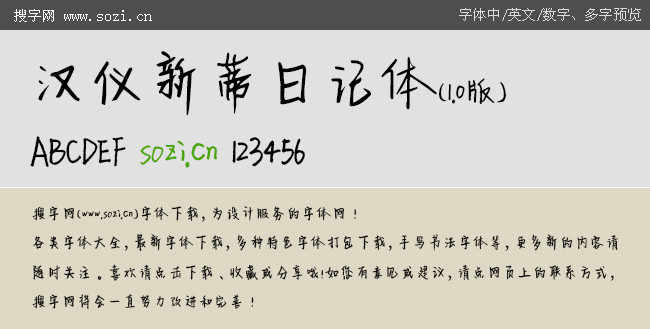
漢儀新蒂日記體1.0
搜字網提供一款漢儀新蒂日記體1.0字體下載,漢儀新蒂日記體是一款漂亮的手寫風格書法字體。由漢儀新蒂工作室出品,漢儀新蒂工作室成立于2016年,由漢儀字庫與新蒂字體聯合成立,本字體字形流暢大方,適合應用于海報設計、藝術設計、包裝設計等應用。(本字體為個人非商用版,如需要商用請聯系漢儀公司購買版權)